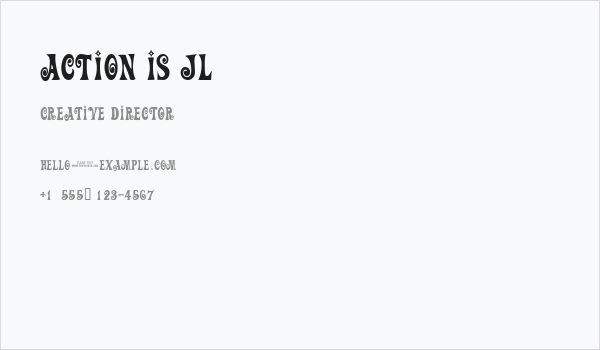
Action Is JL Font
✎ Script
| Anwendungsfall | Headlines, Posters, Artistic Designs |
| Vorgeschlagene Projekte | Ideal for creative projects such as posters, headlines, invitations, and artistic designs that require a lively and dynamic font. |